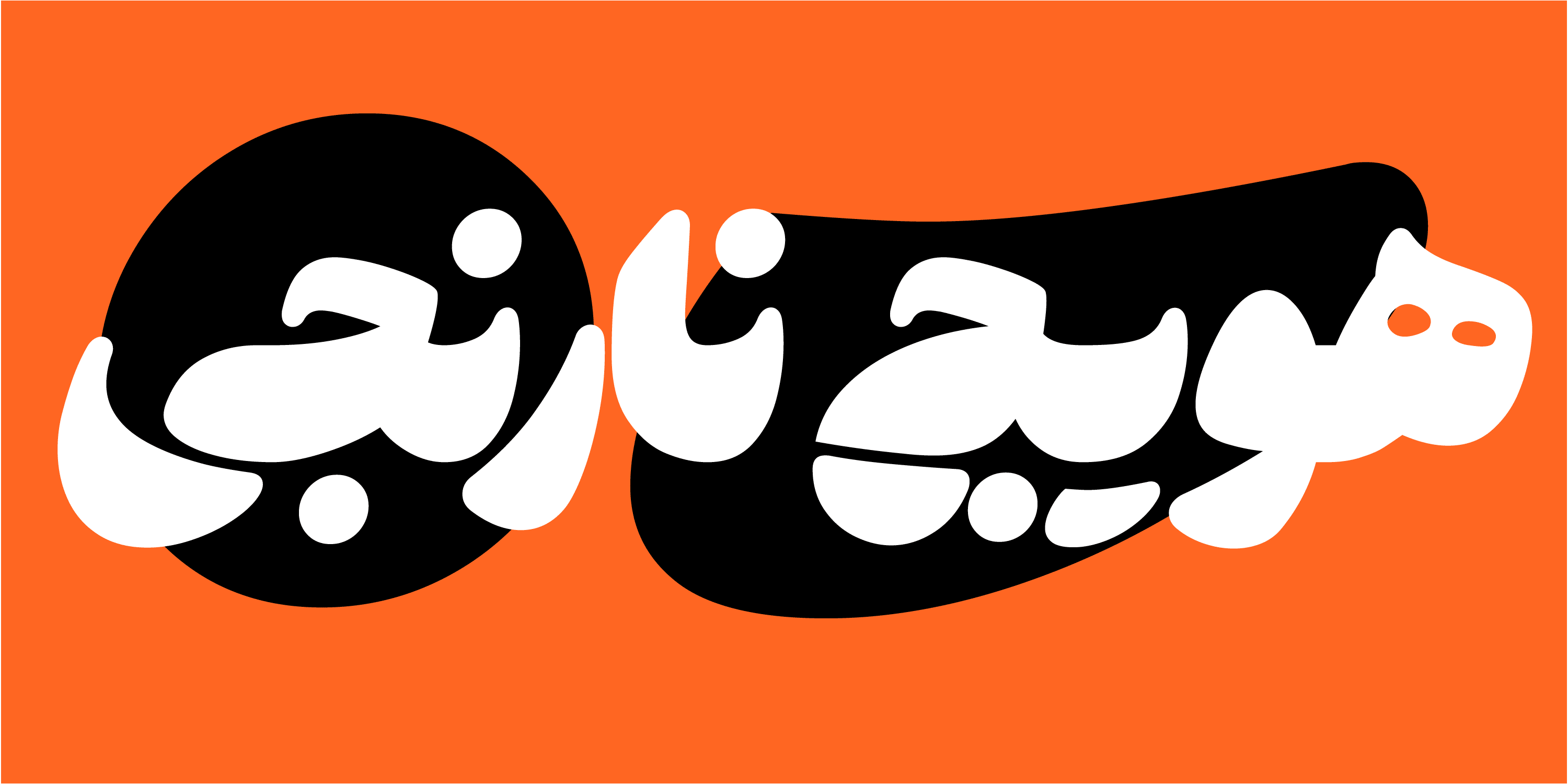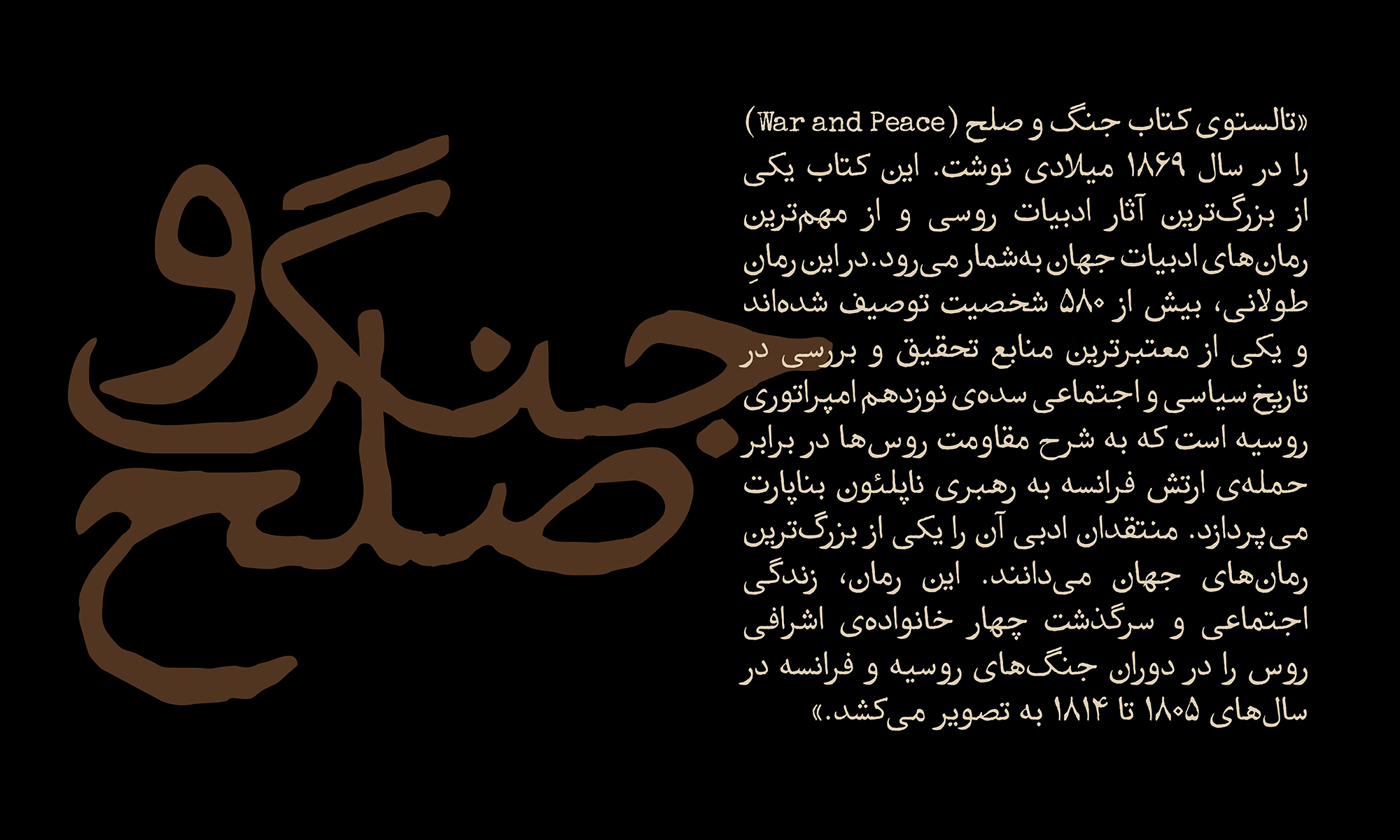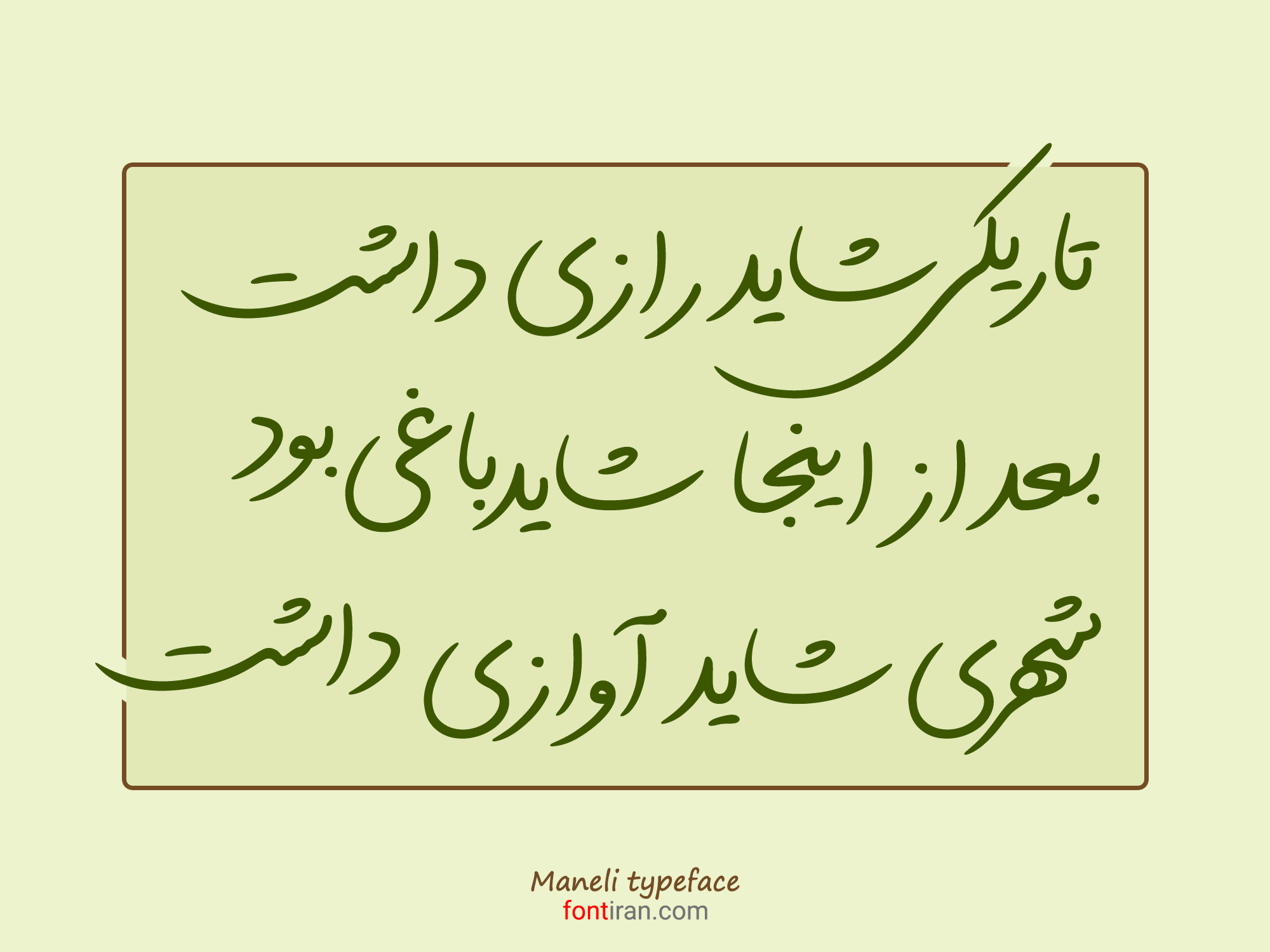
در این پست قصد معرفی فونت های زیبا و لاکچری و خفن رو واسه نرم افزار اینشات داریم . اینشات نرم افزاری با رابط کاربری گرافیکی ساده و قایلیت های فراوان کاربران و علاقه مندان بسیاری داره. شما می تونید با دانلود و نصب فونت های زیبا برای اینشات(inshot)جذابیت و زیبایی دو چندانی رو به تولید و محتوا های خودتون اضافه کنید.
فونت زیبا خودش نصف یک طراحیه . این روزها با پیشرفت تکنولوژی فونت ها و تایپوگرافی فارسی در حال به روز شدن و رفع نقص های نسخه های قبلی و اضافه شدن امکانات جدید به قلم های فارسیه. طراحان این حرفه به دنبال خلق ایده های نو و جدید و پیشرفت هرچه بهتر تایپوگرافی فارسی هستند.
فونت های فارسی دسته بندی های مختلفی داره و استفاده از فونت در نرم افزار اینشات بستگی به نوع کاربرد و محتوای شما داره. این دسته بندی ها متنوعه می تونه فونت های خانواده نسخ – سنس – هندسی دست نویس باشه یا محتواهای مناسب نوشته های رسمی، اساطیری، تاریخی، کودکان تبلیغات نشریات و … توی وبلاگ فونت زیبا هر نوع از فونت و تایپ فیس رو که بخواید موجوده و می تونید دانلود کنید.
ما واستون توی اسلایدر زیر نمونه ای از انواع مختلف فونت های زیبا و خفن رو آماده کردیم . دسته بندی های هر کدوم و کاربردشون و نوع و خانواده شون متفاوته و بسته به سلیقه و محتوایی که قصد ساختنش رو دارید. میتونید دانلودشون کنید. در زیر دسته بندی از بهترین و زیباترین فونت های فارسی برای استفاده در نرم افزار اینشات برای شما عزیزان قرار داده شده که می تونید مشاهده و دانلودشون کنید.
اگه بخواهیم کمی دقیق ترو تخصصی تر به موضوع نگاه کنیم باید این نکته مهم رو بهتون بگم هر نوع محتوایی فونت خودش رو میخاد. این یعنی اگه محتوای شما در باره موضوع کودک و نوجوان هست هر فونتی رو نمیتونید واسه اون انتخاب کنید. و تایپ فیس های مخصوص و نزدیک به این محتوا رو باید انتخاب کنید تا ارتباط لازم رو با مخاطبتون برقرار بکنه. اگه بخوایم یک نمونه مناسب واسه محتوای کودک و نوجوان به شما معرفی کنیم باید به فونت جوان اشاره کرد.
جوان قلمی دست نویس دارای ویژگی نمایشیه. با شور و اشتیاق و رابطه صمیمی که با مخاطبین برقرار می کنه مناسب موضوعات و محتواهای کودک و نوجوانه. به همین منوال واسه سایر محتوا ها هم فونت های مختص کاری اونها وجود داره موضوعات رسمی، محاوره ای ، تبلیغاتی و … فقط کافیه تو سایت ما خوب بگردین.
یکی از قابلیتهای خاص این برنامه چه برای ساخت تصاویر و چه ساخت کلیپهای ویدئویی ، امکان افزودن متن است . حال با افزودن فونت های زیبا و جدید و خفن می توانید زیبایی دو چندانی به تولید محتوا های خود ارائه دهید.فونت ها زیبا رو دانلود کنین واسه اینشات که این امر سبب بازدید و جذابیت بیشتر محصولات شما می گردد.